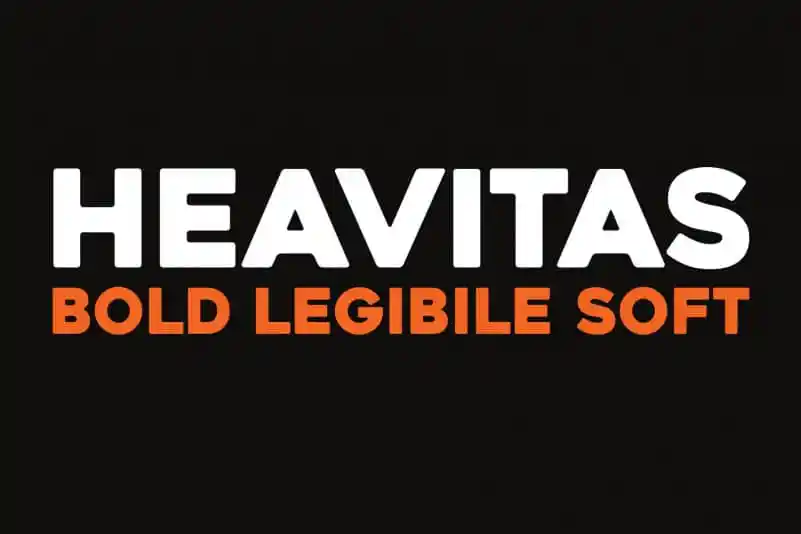
A Heavitas Sans Serif é uma família de tipo geométrico com capas redondas que mantém a razão na criação de cada forma. Seu design permite tanto a utilização exclusivamente dos caracteres maiúsculos quanto os minúsculos, ou até mesmo uma combinação das duas letras para criar um aspecto visual totalmente diferente do tipo. Com sua forte e distinta personalidade, esta fonte é especialmente indicada para logotipos, headlines, marcações, livros, sinalização, gráficos em movimento e embalagens. É uma escolha perfeita para qualquer projeto que busque um estilo contemporâneo e moderno, mantendo ao mesmo tempo um charme sofisticado. Engenhosa e versátil, a Heavitas Sans Serif é o tipo certo para seus projetos que exigem qualidade e originalidade.